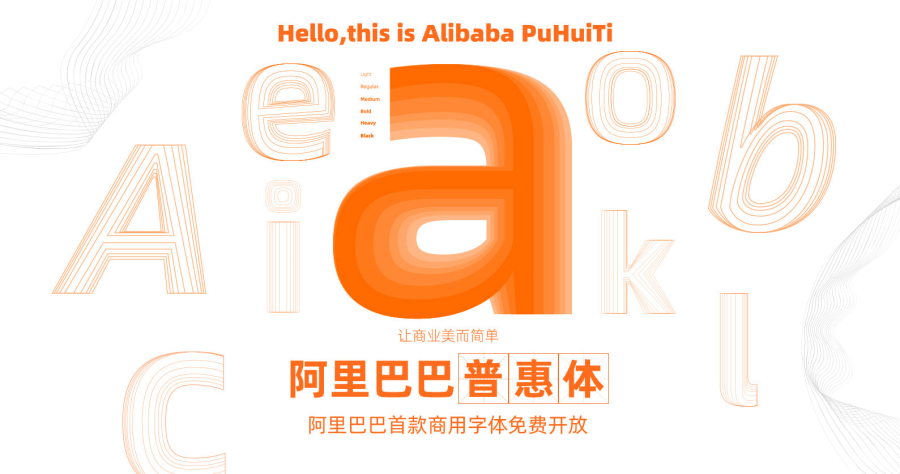
阿里巴巴普惠體 Alibaba Sans 收錄超過 11 萬個漢字,免費下載可商用!
△ 「阿里巴巴普惠體」是一款風格簡約,造型瘦長的字體,重心較一般字體高。適合使用在風格清新、簡約的網頁、設計或海報中!
△ 目前「阿里巴巴普惠體」共收錄 11.6 萬個漢字、7205 個拉丁字,下載包含兩種中英文兩種,英文檔名為 Alibaba Sans。阿里巴巴普惠體可已滿足多種場景中使用需求,雖然為簡體中文,但實測輸入繁體中文也可以使用沒有問題!